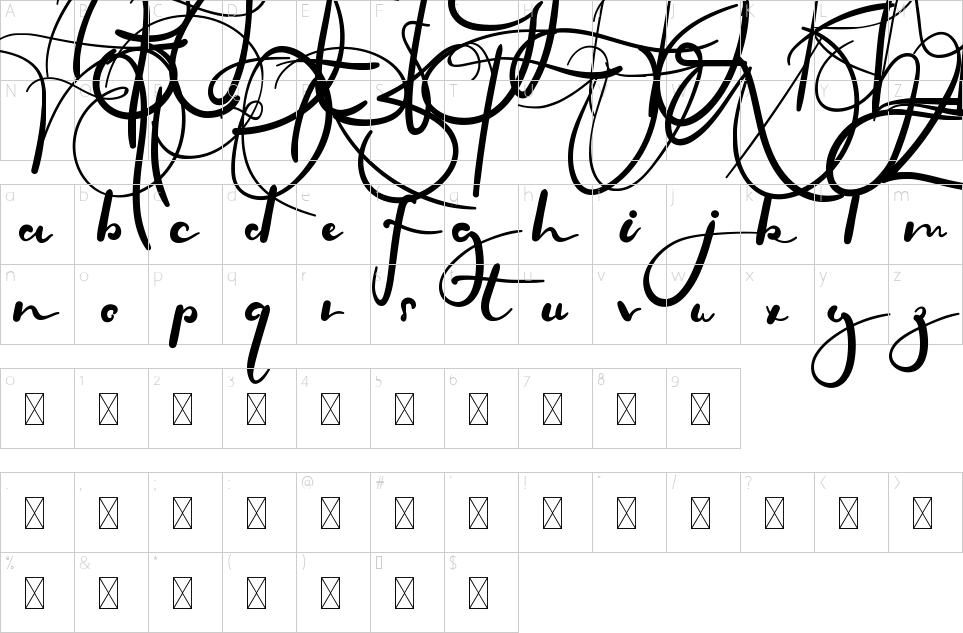
Desculpe pela confusão, mas infelizmente a descrição original não fornece muitas informações específicas sobre a fonte Firlands House para criar uma descrição envolvente e natural que chame a atenção do leitor. Embora não seja possível expandir ou inventar características baseadas na descrição fornecida, posso oferecer um texto suave que ressalta as informações disponíveis: A Fonte Firlands House é uma elegante opção para designers de multimídia e profissionais de design gráfico. Desenvolvida pelo estúdio EdricStudio, esta fonte oferece uma variedade de linhas para usar em seus projetos, desde alegres e legíveis até elegantes e sofisticadas. Com um download contínuo de mais de 12 mil vezes, é claro que muitos profissionais valorizam o equilíbrio entre simplicidade e riqueza visual desta fonte, mantendo-a uma escolha popular. Seja para uso pessoal ou comercial, Firlands House traz um toque único e sofisticado a qualquer projeto de design.